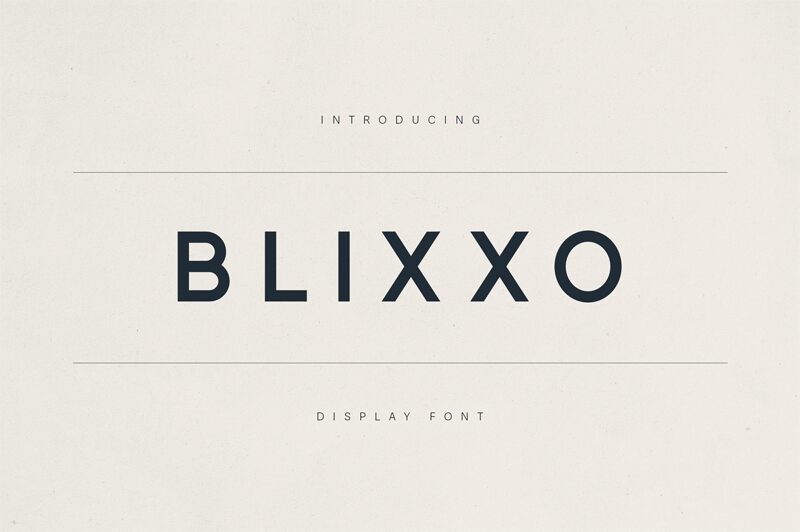
Blixxo Demo Regular
Blixxo es una tipografía geométrica sans serif gratuita, definida por cambios abruptos entre bloques verticales contundentes y diagonales cruzadas muy afiladas. Esta mezcla dota a las letras de un ritmo recortado y de alto contraste, donde las formas de lados rectos se sienten casi como una señalización y las estructuras en X repetidas introducen un patrón de diamante marcado.
La fuente encaja a la perfección en pósteres, arte de álbumes, gráficos de streetwear, logotipos y titulares cortos donde la repetición angular puede sustentar el diseño. Su uso más potente es en aplicaciones de display, ya que sus siluetas rígidas y diagonales enfáticas crean una textura memorable sin necesidad de adornos adicionales.